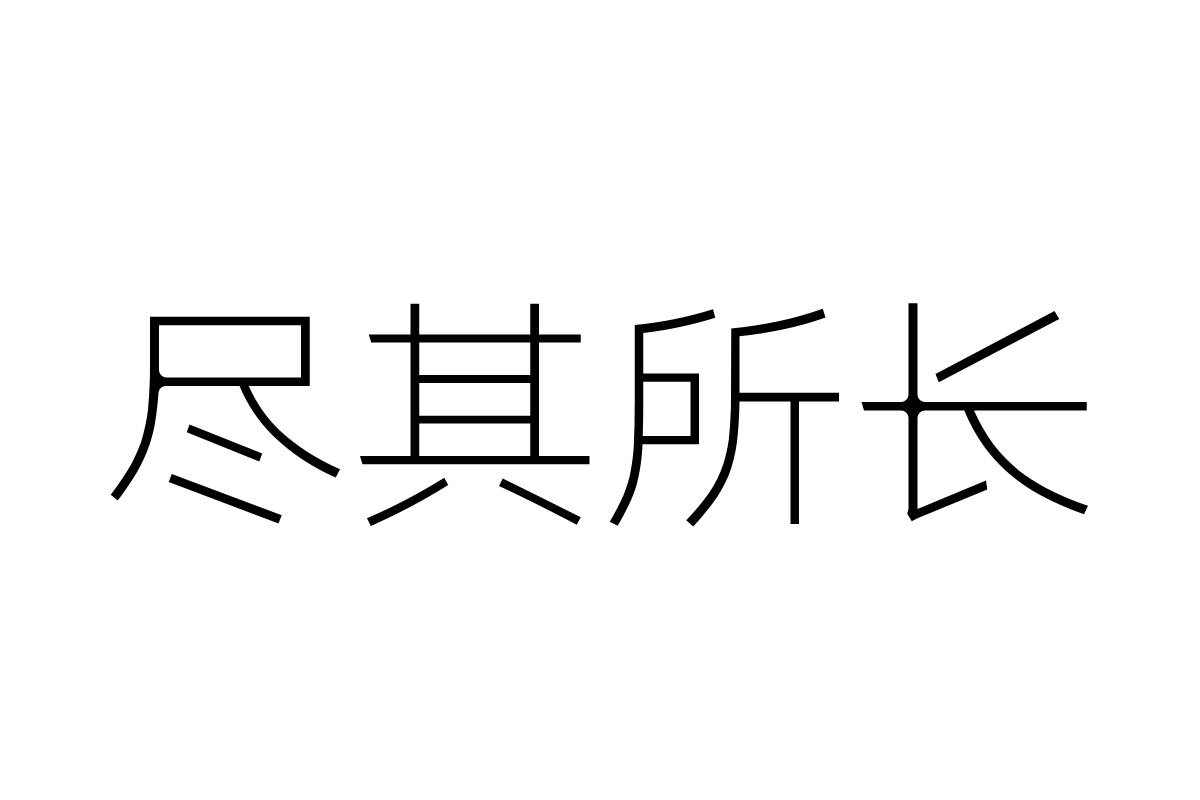
三极铜线黑简体-细是一种字体,主要用于印刷和设计领域。这种字体的特点是线条清晰,笔画流畅,适合用于制作书籍、杂志、报纸等印刷品。同时,由于其线条粗细适中,也适合用于制作网页、海报等设计作品。
三极铜线黑简体-细的笔画粗细适中,既有粗犷的感觉,又有细腻的韵味,给人一种沉稳而不失灵动的感觉。这种字体的特点是线条清晰,笔画流畅,非常适合用于需要强调文字内容的场景。
此外,三极铜线黑简体-细的字形结构紧凑,整体感强,使得阅读起来更加方便。同时,它的字形大小适中,既不会显得过于庞大,也不会显得过于细小,适合各种尺寸的印刷品。
总的来说,三极铜线黑简体-细是一种实用性很强的字体,无论是在印刷还是设计领域,都有很好的应用前景。